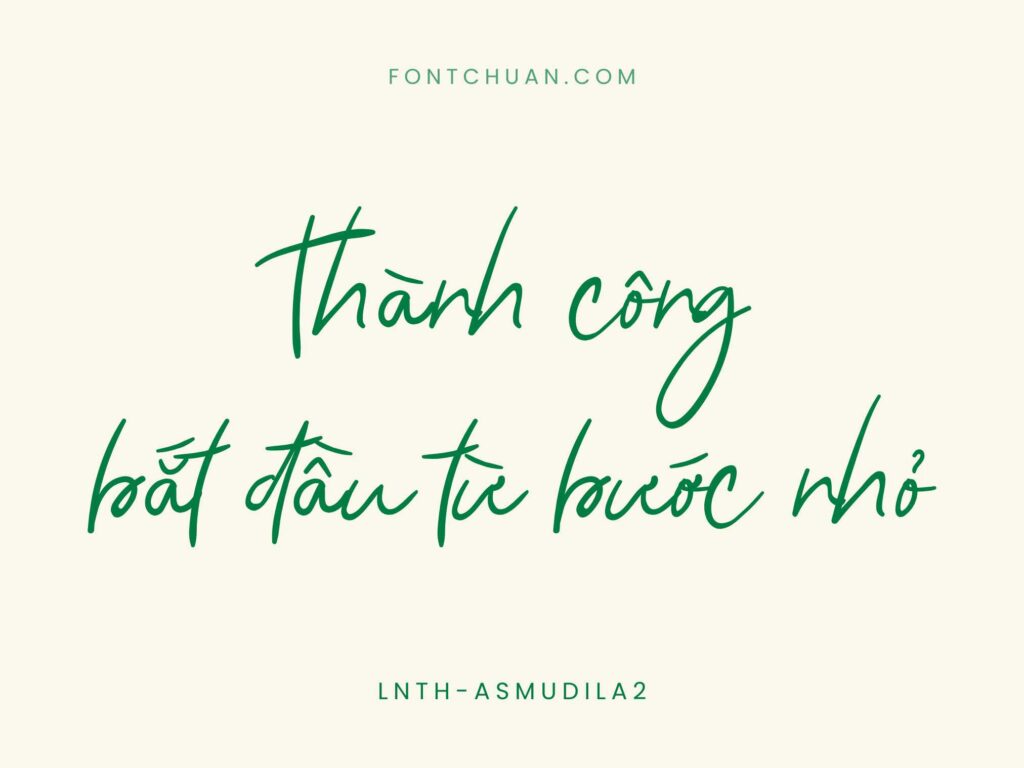
Font LNTH Asmudila Việt Hóa
Tác giả Font: Lyanatha
Asmudila là một phông chữ viết tay được thiết kế bởi lyanatha, mang phong cách tự nhiên và mềm mại. Phông chữ này tạo cảm giác thân thiện và gần gũi, phù hợp cho nhiều dự án thiết kế cần sự ấm áp và cá nhân hóa. Nhờ được Việt hóa bởi LNTH, Asmudila hỗ trợ đầy đủ các ký tự tiếng Việt, giúp người dùng dễ dàng áp dụng trong các dự án đa ngôn ngữ. Phông chữ này được sưu tầm và đăng tải bởi thành viên của Font Chuẩn nhằm đáp ứng nhu cầu đa dạng của cộng đồng thiết kế.
Về đặc điểm thiết kế, Asmudila có các ký tự được vẽ tỉ mỉ với những đường nét mượt mà, tạo nên phong cách viết tay tự nhiên nhưng không kém phần tinh tế. Phông chữ này đặc biệt phù hợp cho các dự án như thiệp mời, bìa sách, poster, logo và các ấn phẩm quảng cáo, giúp truyền tải sự thân thiện và nghệ thuật.
Với các nét chữ uyển chuyển, Asmudila còn có thể được sử dụng như một Font chữ ký, lý tưởng cho các logo cá nhân, thiệp cưới hoặc các dự án cần dấu ấn riêng biệt, tinh tế và sang trọng. Ngoài ra, Asmudila cũng thích hợp cho các sự kiện như lễ hội, sinh nhật, Valentine và Trung thu, mang đến không gian ấm áp và lãng mạn. Trong lĩnh vực ngành nghề, phông chữ này được ứng dụng rộng rãi trong quảng cáo, thiết kế thiệp cưới, giáo dục và công nghệ, góp phần tạo điểm nhấn độc đáo và chuyên nghiệp cho các sản phẩm và thương hiệu.